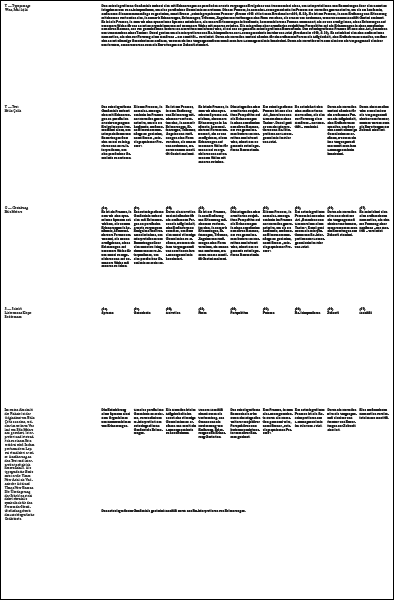
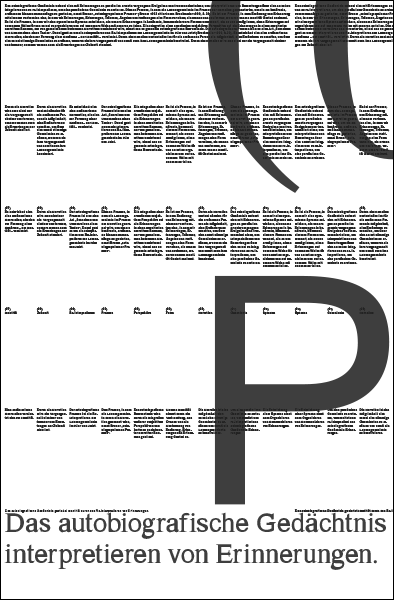
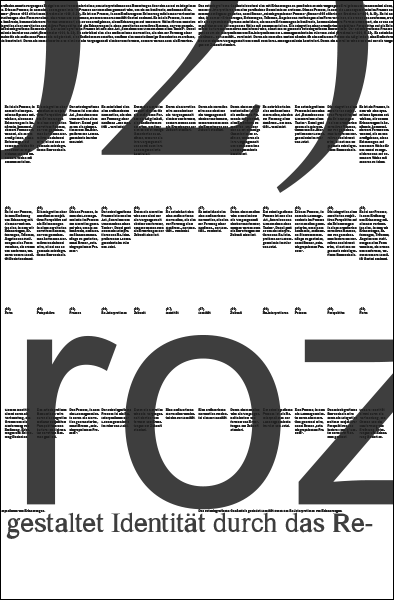
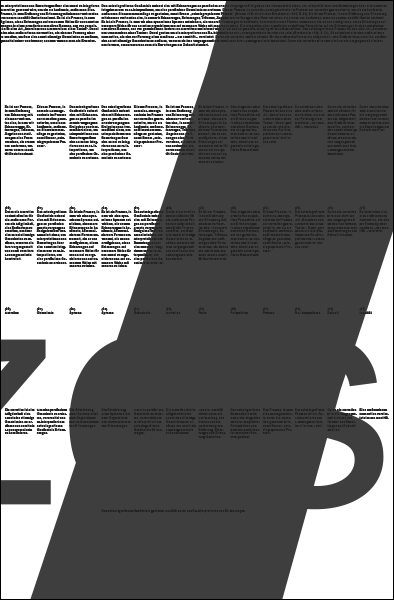
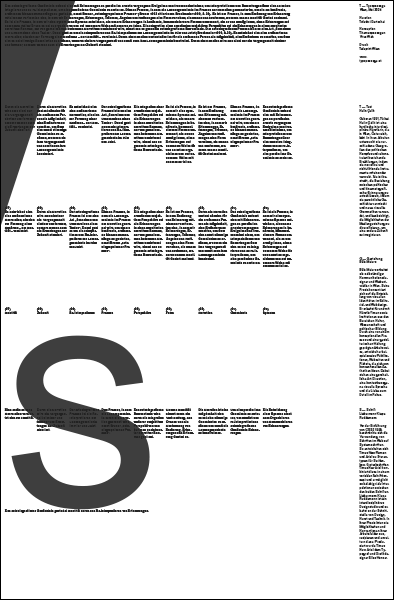
Im ersten Abschnitt der Plakate ist der Originaltext von Helin Çelik zu sehen, welcher im weiteren Verlauf von Béla Meiers neu geordnet, interpretiert und letztendlich zu einem Satz verkürzt wird. In dem performativen Layout visualisiert er seine Annäherung an den Text und interpretiert zeitgleich dessen Inhalt. Als typografische Basis nutzt er die Times New Arial als Variante der Arial und Times New Roman. Die Überlagerung der Schriften steht dabei ebenfalls symbolisch für den Prozess der Identitätsfindung durch das autobiografische Gedächtnis.
Typografie
Liebermann Kiepe Reddemann. Vor der Einführung von CSS2 1998 beschränkte sich die Verwendung von Schriften im Web auf Systemschriften. So entwickelten sich Times New Roman und Arial zu Stereotypen für Serifen- bzw. Groteskschriften. Times New Arial kombiniert diese in einem variablen Schriftkonzept und ermöglicht so beliebig viele Interpolationen zwischen den beiden Schriften. Liebermann Kiepe Reddemann ist ein interdisziplinäres Designstudio und arbeitet an der Schnittstelle von Design, Kunst und Technik. In ihrer Praxis loten sie Möglichkeiten und Kon- ventionen ihrer Arbeitsfelder aus, rezipieren und erweitern diese. Produziert wurde Times New Arial von Typograf und Grafikdesigner Elias Hanzer. liebermannkiepereddemann.de